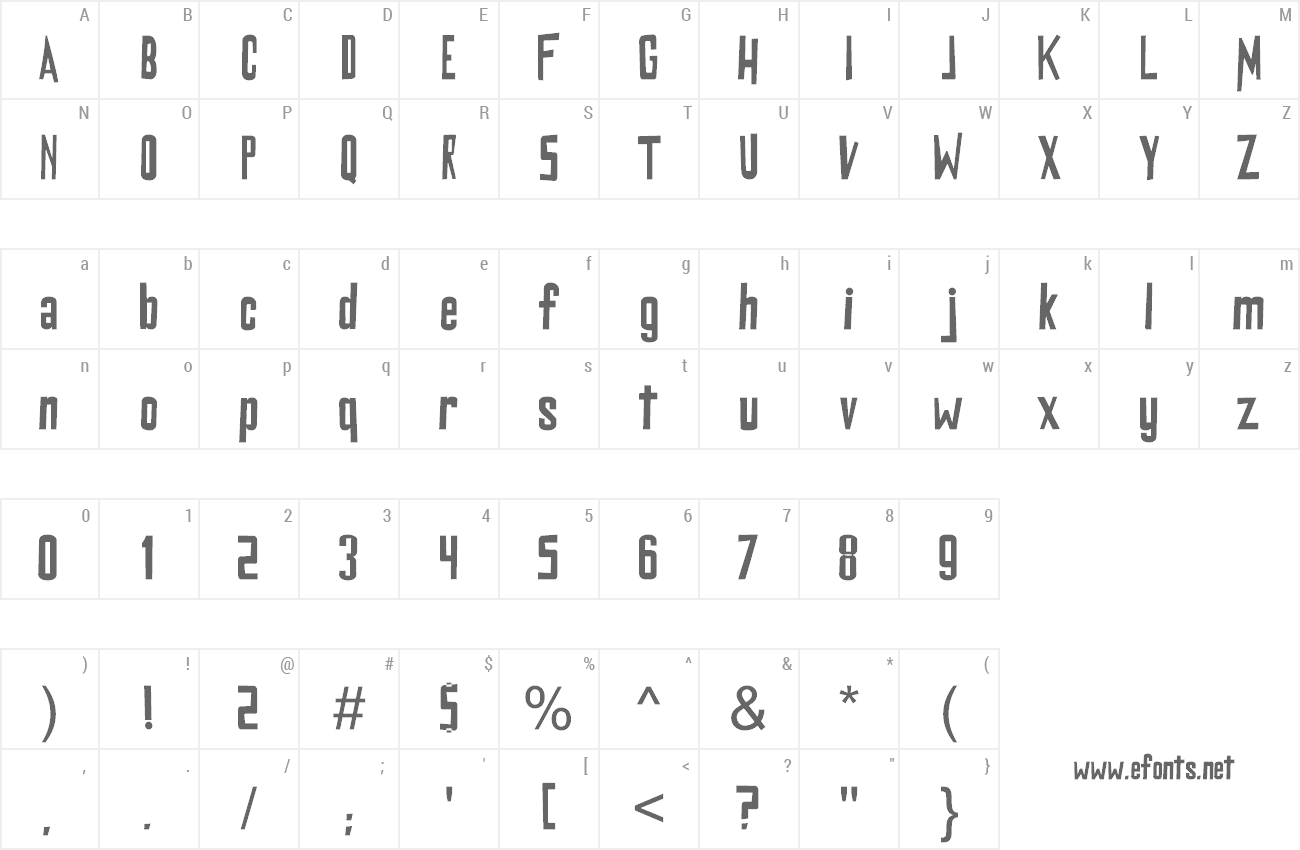
| Font name: | DiGrado |
| Author: | SeaTypes |
| Note by SeaTypes | |
Fonte criada a partir da ilustração das letras desenhadas por Vicente Di Grado para as capas dos livros da Editora clube do Livro, durante a década de 1960, no Brasil. Informações adicionais sobre o trabalho podem ser vistas em: https://goo.gl/ogZY9T |